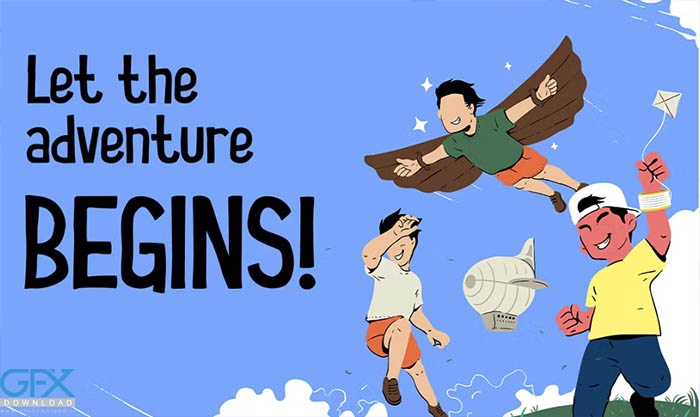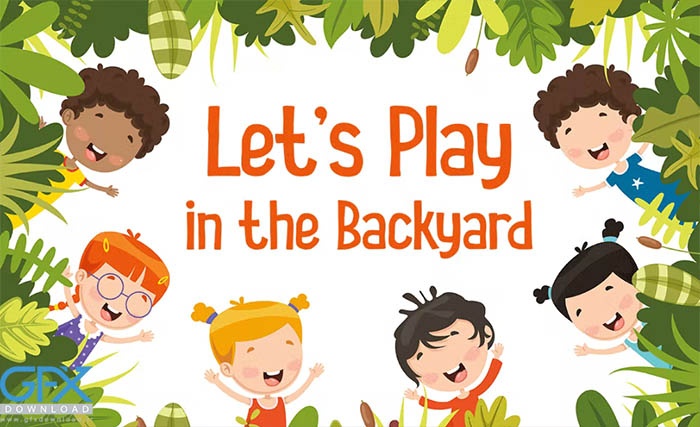
مناسب انواع طراحی های کودکان شامل آلبوم کودک،بنر،کارت دعوت تولد کودکان و سایر طراحی های کودکانه دیگر می باشد. دانلود رایگان فونت کودکانه Courage Kid یک فونت سرشار از شادی و شجاعت برای کشف دنیایی جدید. خطوط ناقصی که حروف را می سازند، نمونه کاملی از پیشرفتی است که در زندگی داشته اند.
فونت انگلیسی کودکانه Courage Kid
این فونت انگلیسی رایگان بچه ها Courage Kid مناسب برای بازار کتاب های کودکان، بازی های آنلاین، پوسترهای رویداد، فونت وسایل مدرسه، پوسترها، عنوان فیلم ها، جلدهای یوتیوب، تصاویر کوچک یوتیوب، جلد صفحات رسانه های اجتماعی و غیره...